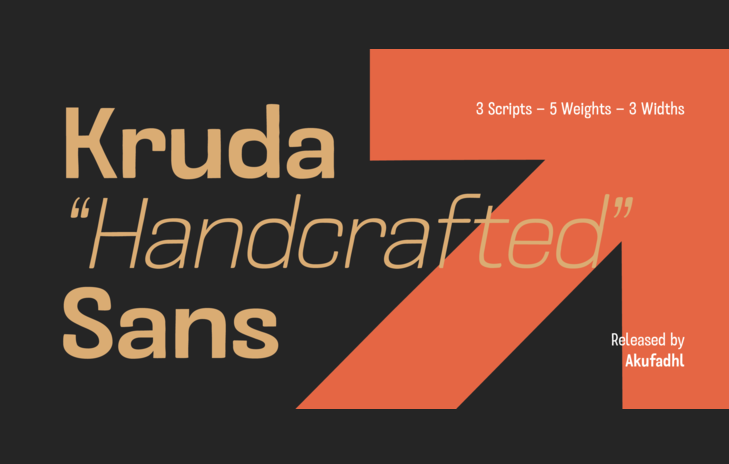
Aqui está uma descrição em português para a página de download da font ‘Kruda Font Family’: Olá! Esta é uma família de tipografia sans serif. Agradecemos pela sua atenção à Kruda Typeface, um tipo-display gráfico sem formar desenvolvido cuidadosamente e inspirado na antiguidade de um grotesco encontrado em placas velhas. Esta fonte vem com três larguras diferentes e cinco pesos para atender às necessidades de vários contextos tipográficos. Ela também inclui uma versão inclinada, que adicionará flexibilidade ao seu design. O conceito original para Kruda era um tipo específico destinado à nossa família Naratif, mas acabou se transformando em algo mais profundo e autêntico. Ao longo deste processo, decidimos ampliar a linguagem suportada: agora incluímos suporte para o alfabeto latino, cirílico e grego. Queremos compartilhar Kruda com você porque entendemos que cada tipo pode ter uma história única, inspiradora e diversificada. Acreditamos que esta família de fontes é um excelente exemplo disso. Esperamos que ela se torne parte importante do seu design gráfico, ampliando sua linguagem visual para incluir novos idiomas e estilos. Descubra mais sobre Kruda Typeface e descarregue sua cópia hoje!